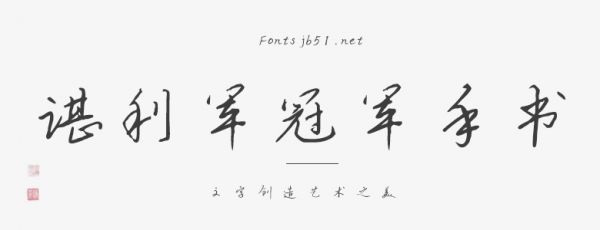
諶利軍冠軍手書(shū)由東京奧運(yùn)會(huì)舉重男子67公斤級(jí)冠軍諶利軍創(chuàng)作。這款字,筆鋒沉穩(wěn),霸氣,體現(xiàn)了屬于體重冠軍的獨(dú)有力量。該字體適用于雜志、書(shū)刊,品牌廣告和產(chǎn)品包裝設(shè)計(jì),以及社交網(wǎng)絡(luò)的個(gè)性化用字。